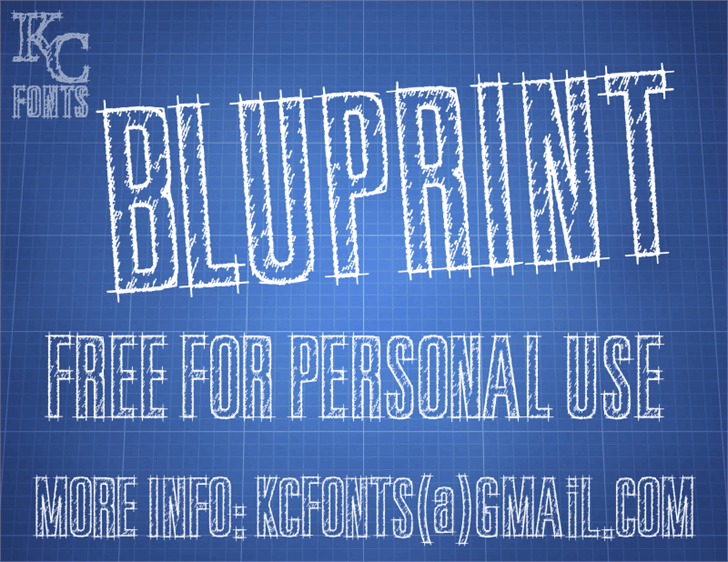
A Bluprint é uma fonte simbólica que oferece aos designers um toque natural e envolvente no design do seu projeto. Desenhada pelo talentoso Hamilton, essa fonte captura a essência de cada letra com sutileza e elegância, o que torna-a perfeita para qualquer aplicação pessoal ou projetos de hobby. Com sua capacidade única de criar texturas vívidas e interessantes, a Bluprint se destaca em designs digitais variados. Seu uso não só dá um toque único aos seus design gráficos, mas também adiciona uma dose de personalidade às suas criações. Esta fonte é ideal para designers que buscam algo mais do que apenas linhas retas e formas geométricas convencionais. Ela oferece ao designer a liberdade de explorar diferentes estilos sem ter de recorrer a outras fontes, proporcionando uma experiência única em cada projeto. Com sua versão comercial disponível, a Bluprint está aqui para tornar seu design único e inovador.